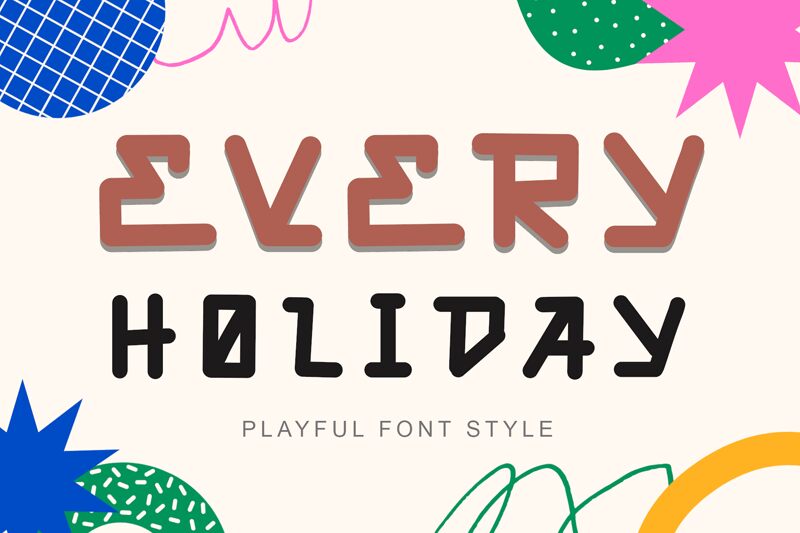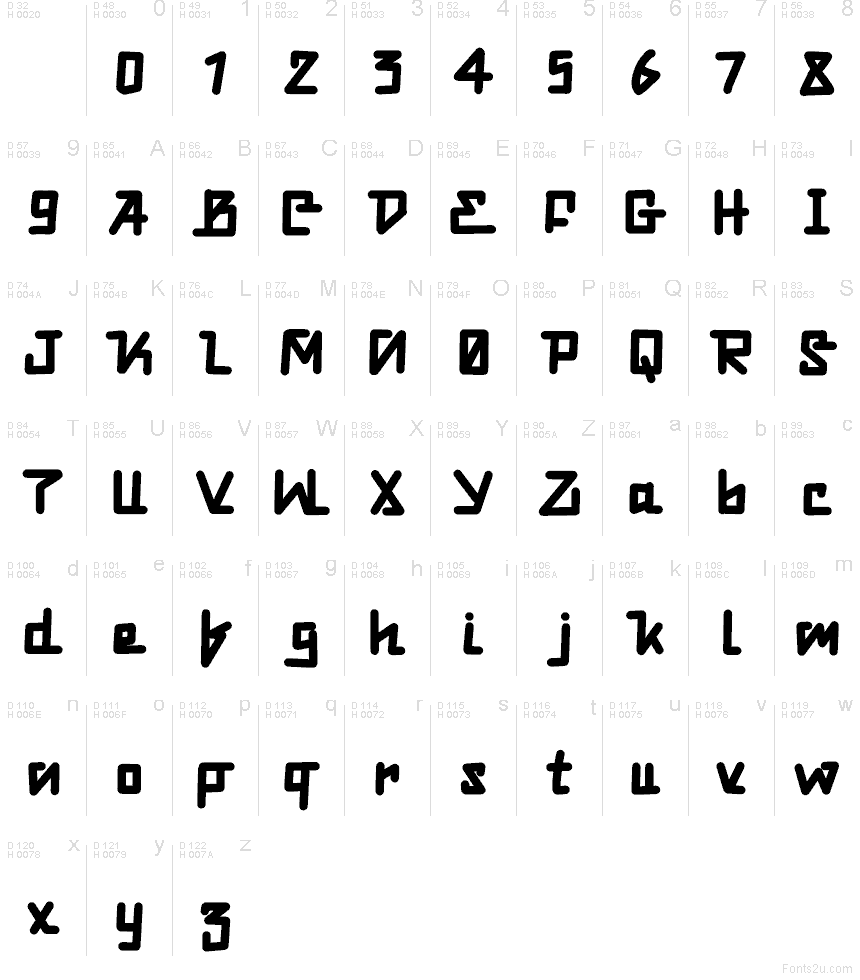
Every Holiday Demo
Every Holiday od Every Holiday je bezplatné display písmo so zaoblenými, nepravidelnými geometrickými tvarmi a jemným, mierne vykrojeným spracovaním hrán. Písmená pôsobia ručne vyrobeným, ale premysleným dojmom – s širokými krivkami, zahnutými rohmi a špecifickým rytmom, ktorý dodáva nápisom pohyb.
Every Holiday sa skvele hodí na blahoželania, pozvánky na večierky, sezónne obaly, titulky plagátov, etikety a scrapbooking, pretože jeho tvary nesú sviatočnú, osobitú atmosféru bez toho, aby pôsobili rušivo. Toto bezplatné písmo sa hodí aj pre akcenty v logách a krátke nadpisy, kde môže zaoblený display štýl dodať dizajnu priateľský a neformálny nádych.